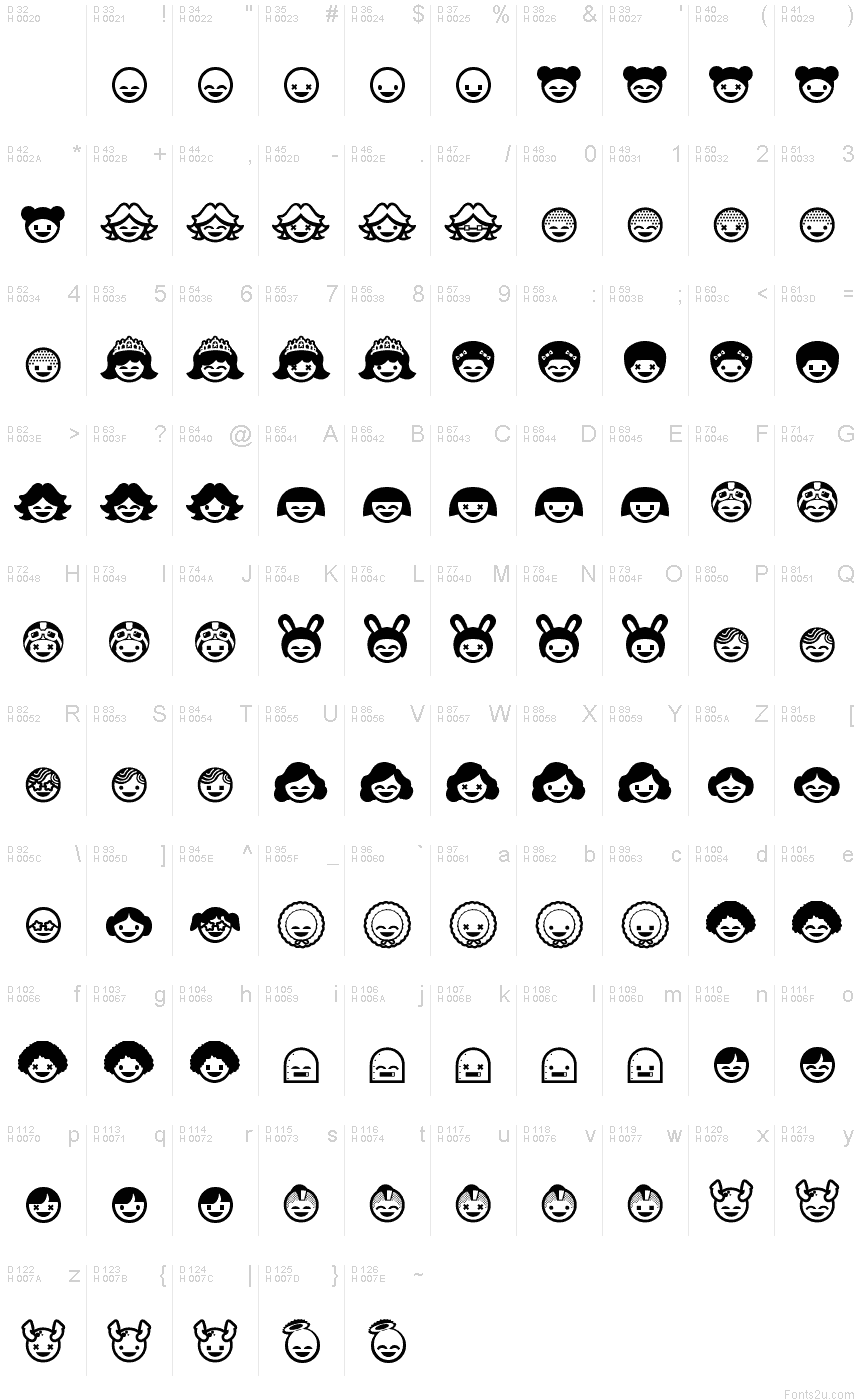
Ski Pop от Fontalicious Fonts — это бесплатный дингбат-шрифт с мультяшными лицами, передающий дерзкое настроение стикеров начала нулевых. В наборе — смелые круглые головы, простые глаза-точки, дурашливые ухмылки и несколько вариантов с невозмутимым выражением лица. Настроение варьируется от милого и пустого до слегка озорного, но шрифт не теряет своей простоты и «игрушечного» характера.
Он отлично подходит для молодежных флаеров, заголовков для скрапбукинга, приглашений на вечеринки, зинов и игривого мерча, где шрифт может выступать скорее как набор маленьких персонажей, чем как буквы. Используйте его для коротких надписей, значков, оформления заголовков или подписей в классе, когда нужны лица, которые легко читаются и задают легкий тон.